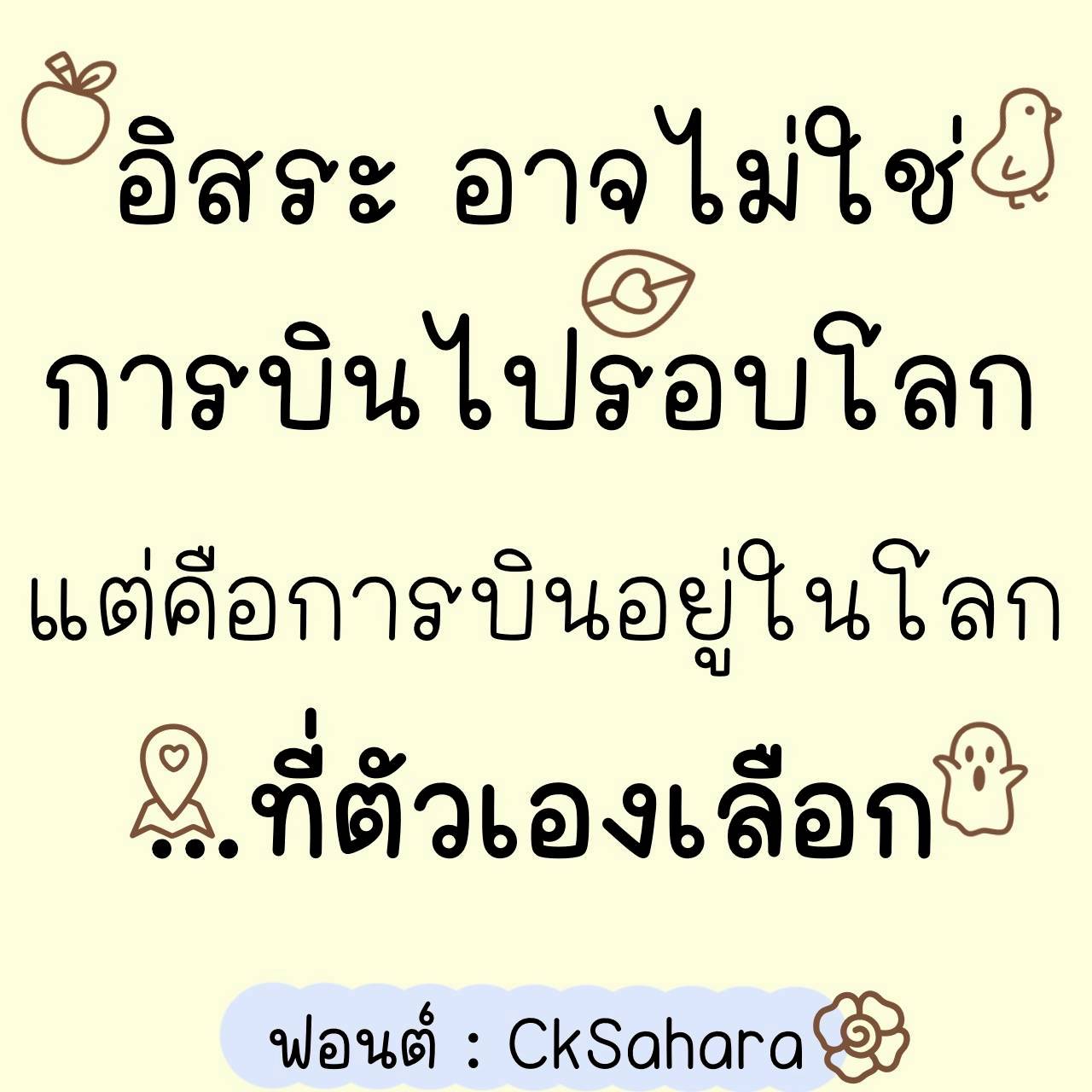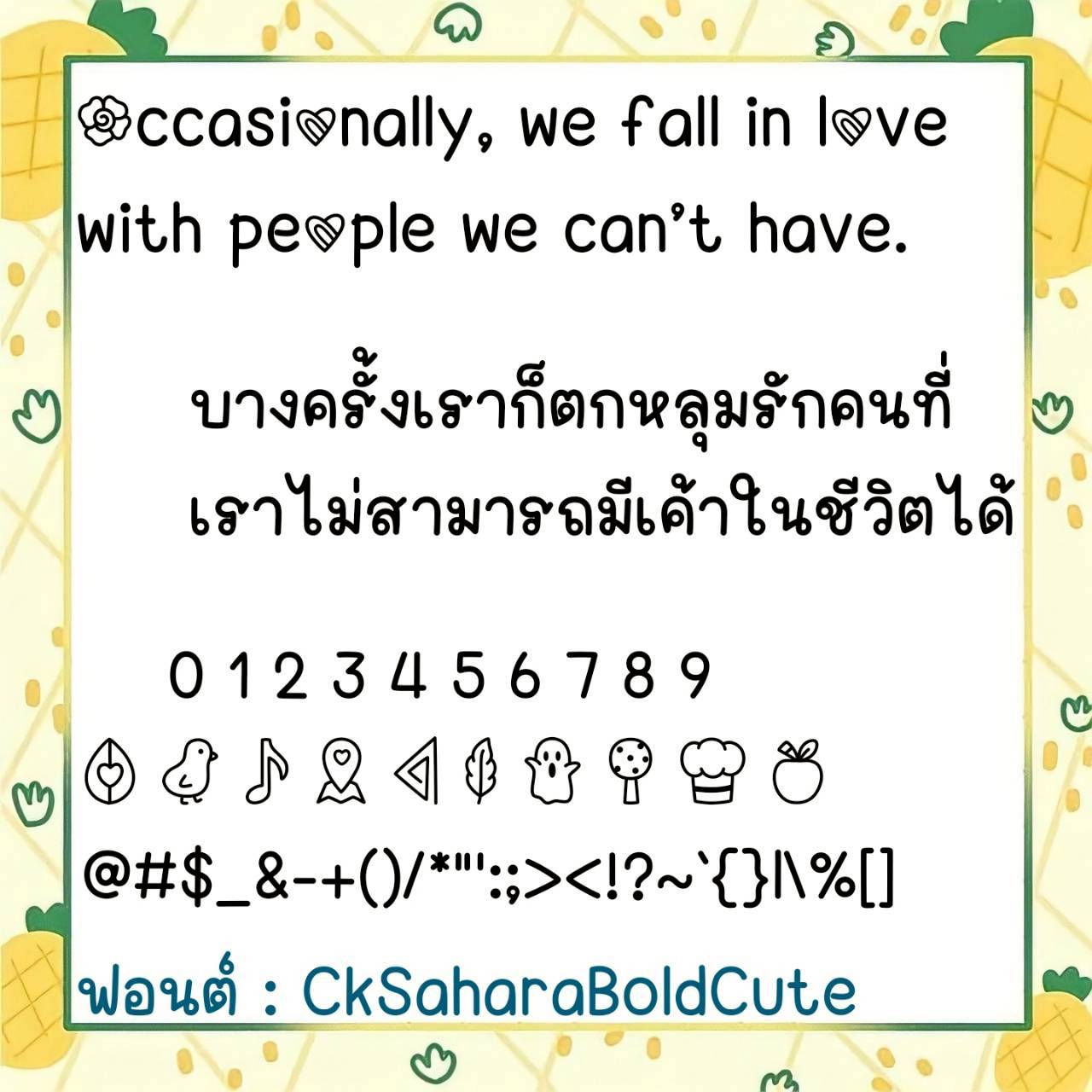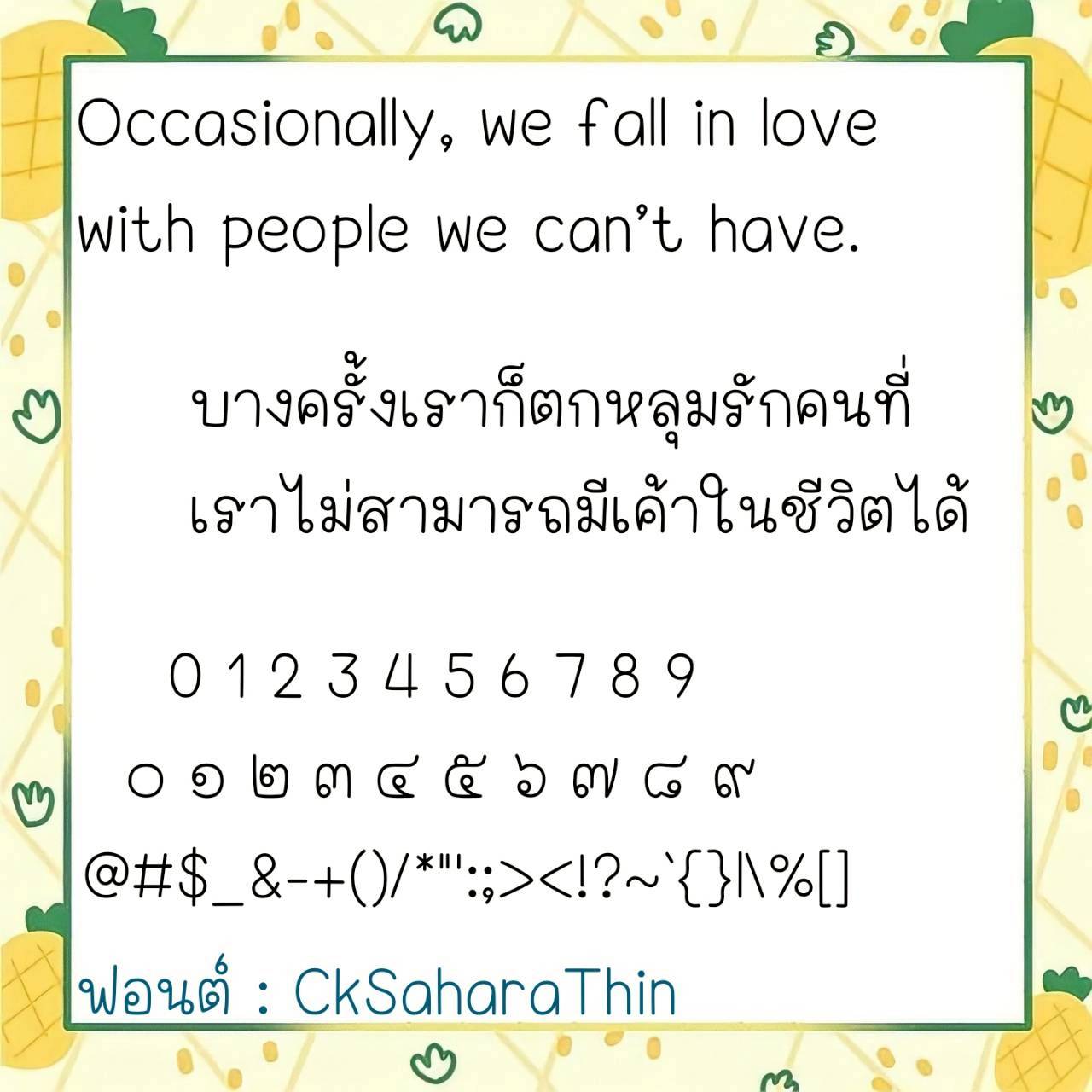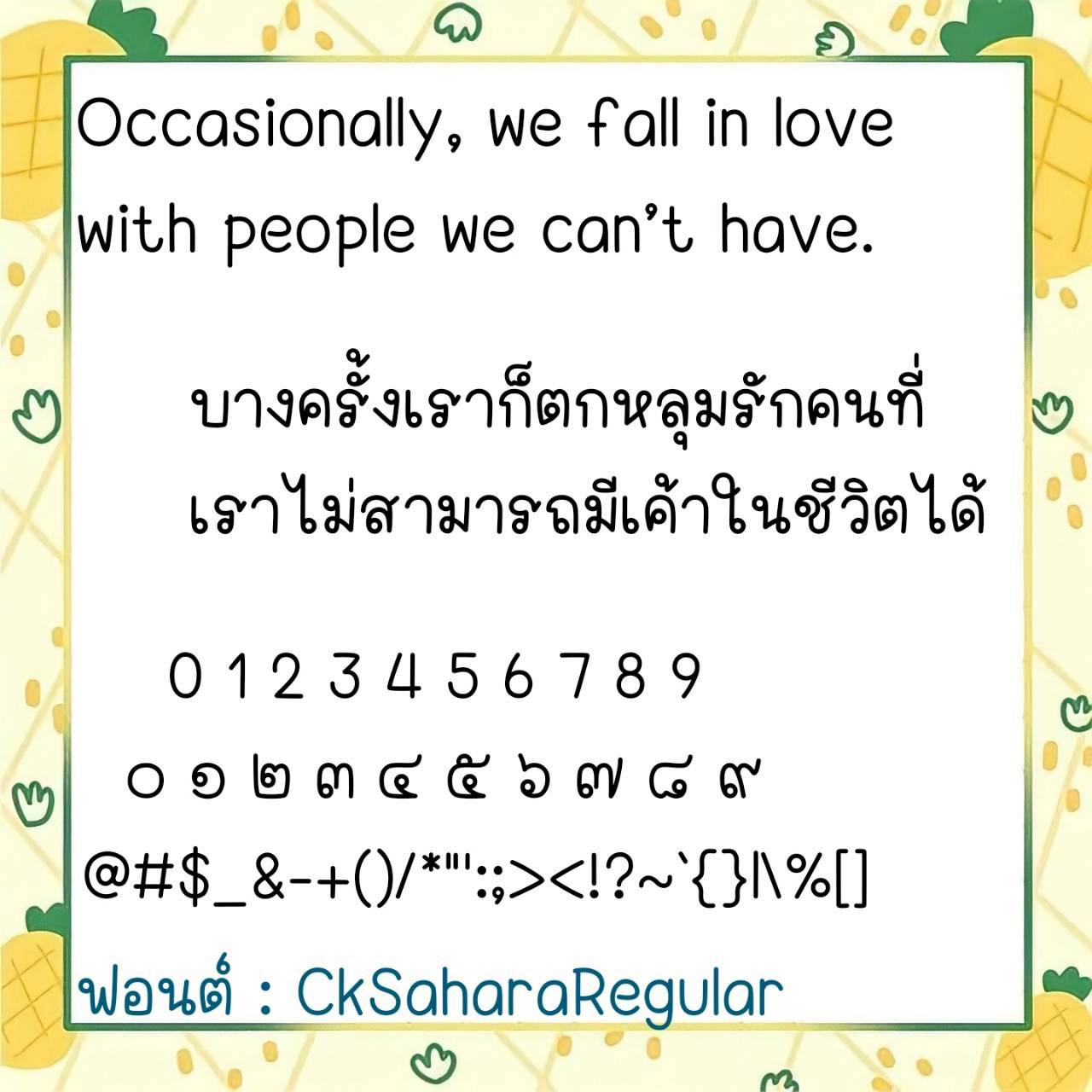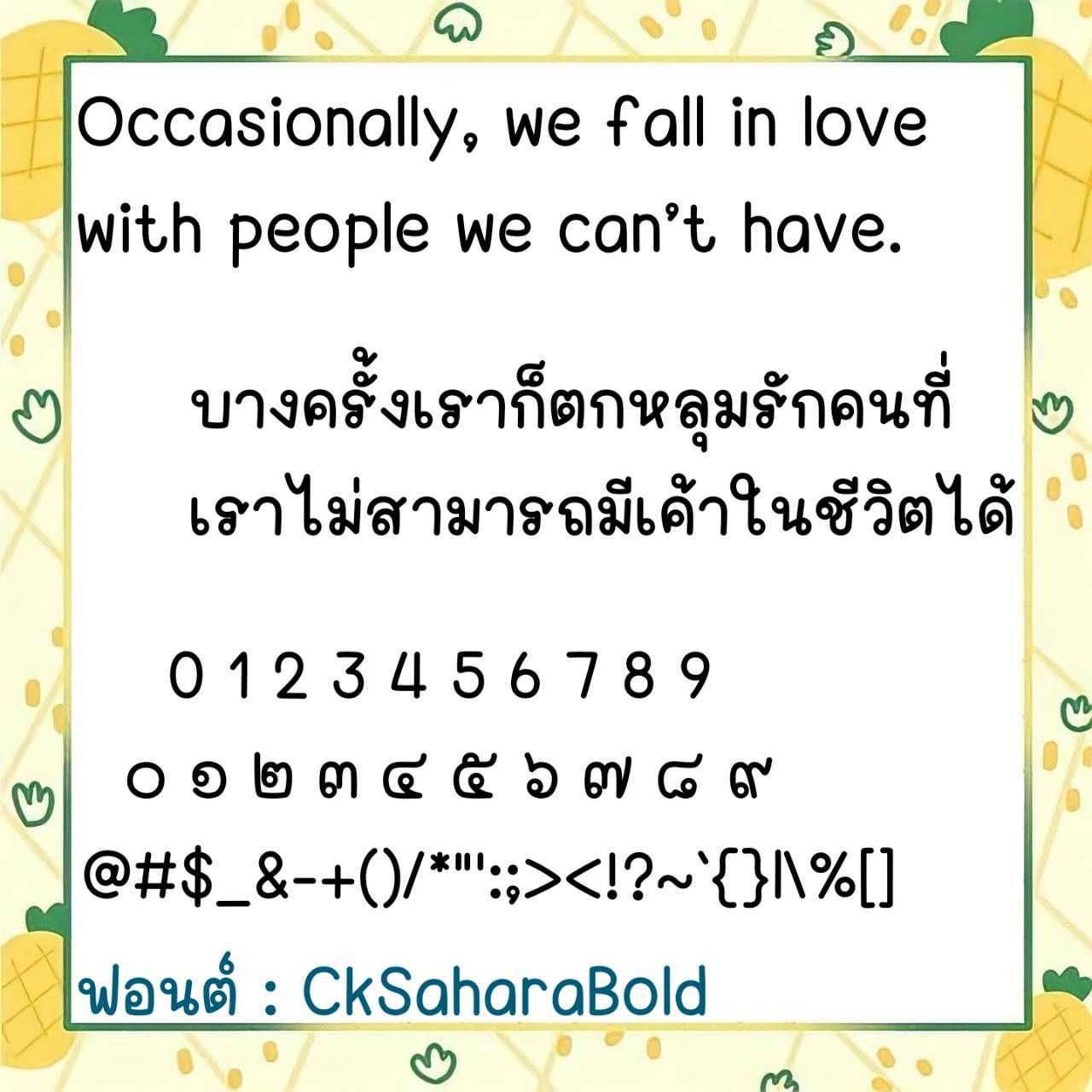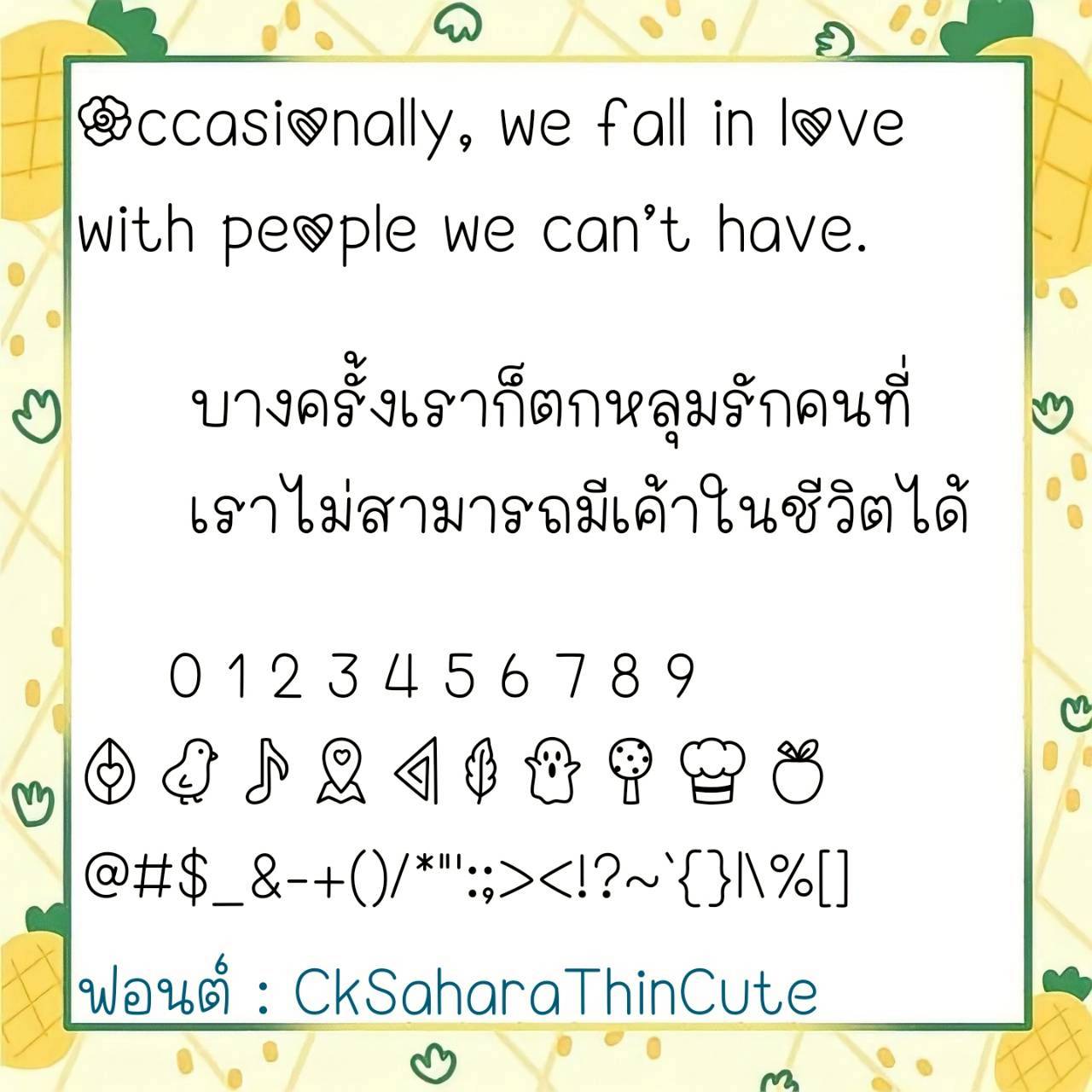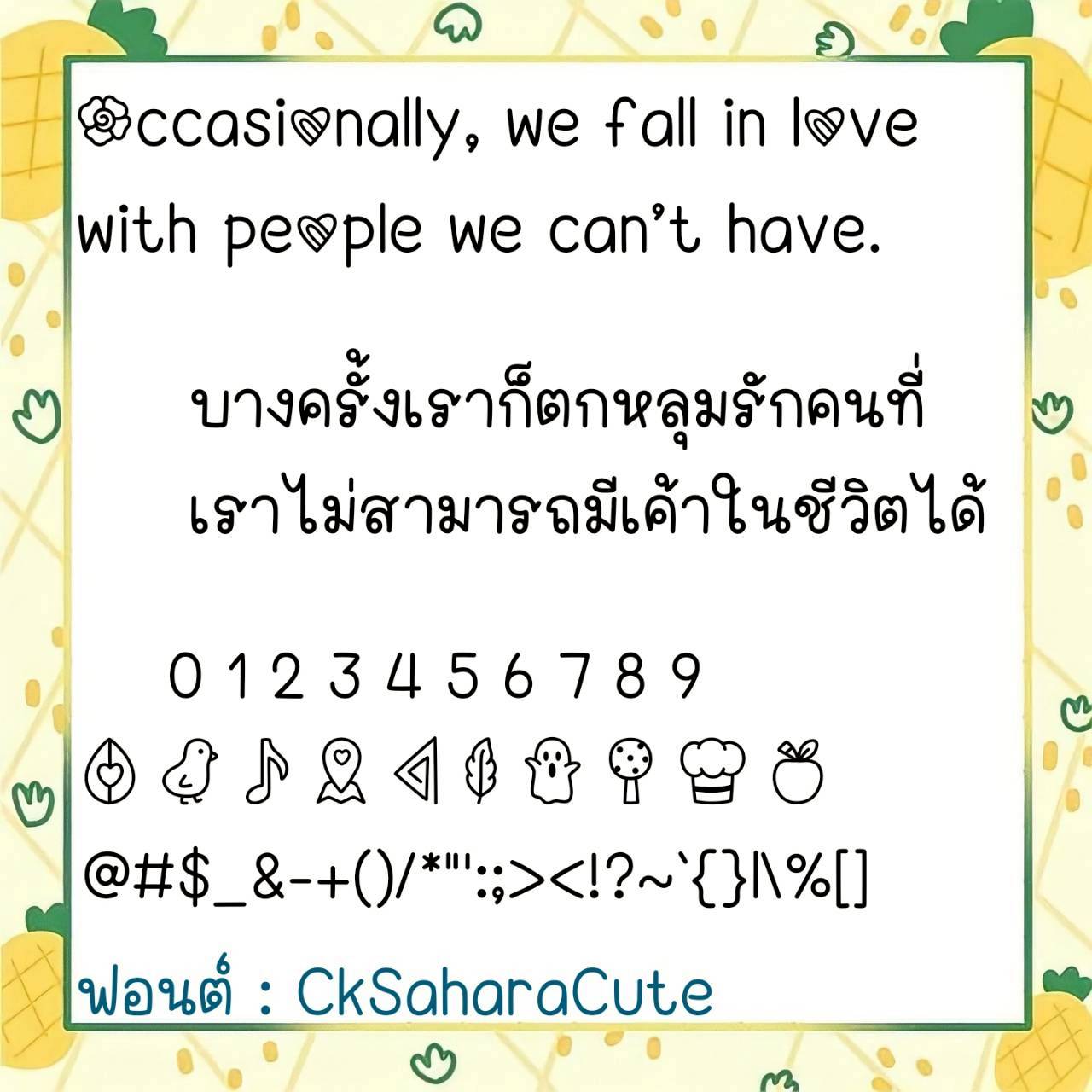
Font CkSahara
🔸 ฟอนต์ลายมือแนวน่ารัก ตัวกลมๆอวบอ้วน สไตล์วัยรุ่นดูไม่น่าเบื่อ เน้นอ่านง่ายสบายตา และยังมีไฟล์อิโมจิน่ารักๆที่ใช้แทนเลขไทยให้ด้วยค่ะ 🥰💙
🔹 A cute, handwritten font with round, chubby characters in a youthful style that’s anything but boring. It’s easy to read and visually appealing, and it also includes cute emoji files to replace Thai numerals. 🥰💙